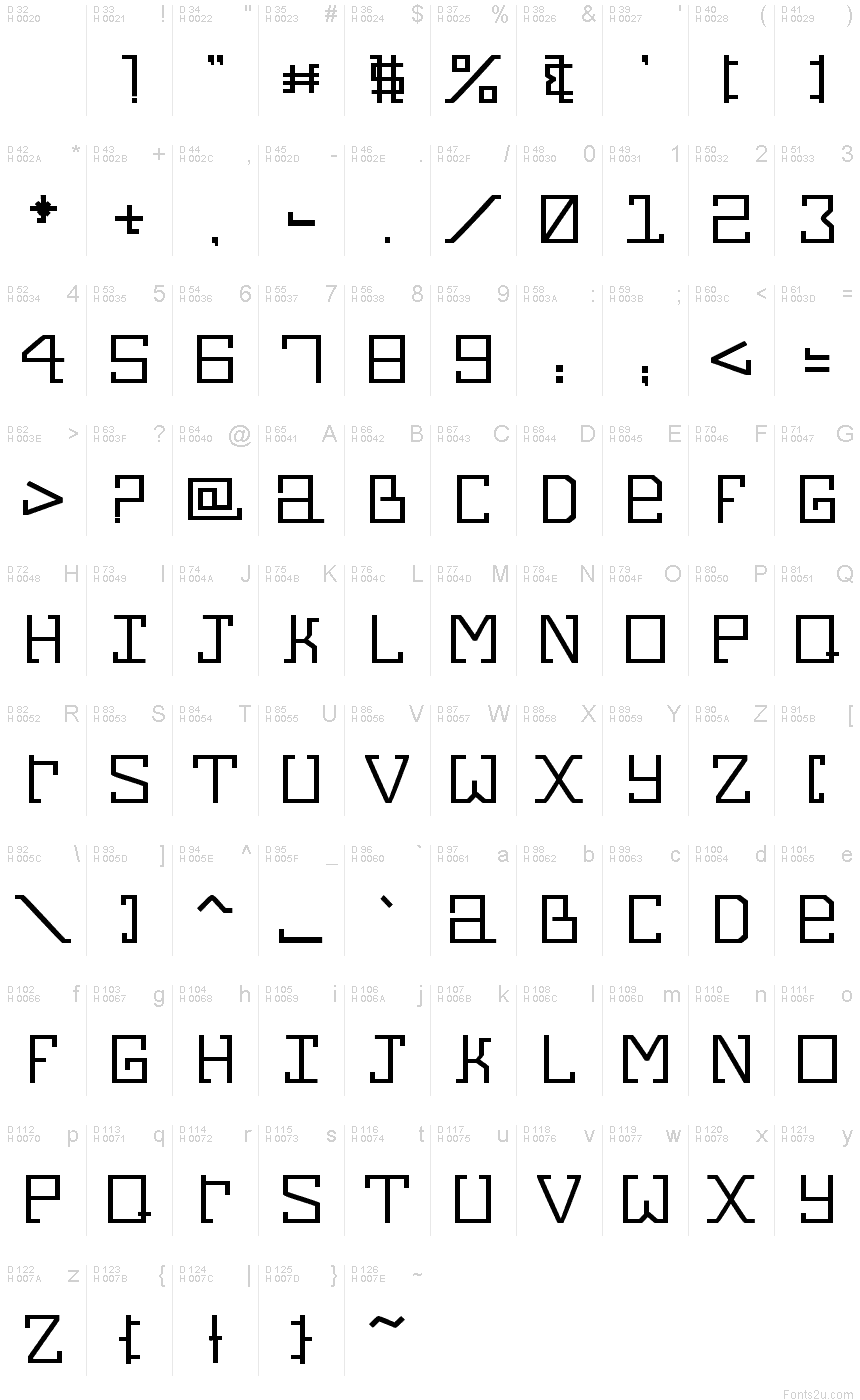
由 Zogoz 的 Andrew Hungerford 设计的 Alphecca 是一款免费的科技感显示字体,看起来就像直接从数字网格中雕刻出来的一样。它的字母高挑、方正,结构紧凑,锋利的 90 度转角既有机械感又出奇地清晰易读。均匀的笔画粗细带来了霓虹灯般的视觉清晰度,赋予每个单词冷静、严谨的工程美感。
使用 Alphecca,您可以打造出适用于科幻界面、游戏 Logo、合成器波(synthwave)海报、科技活动传单以及未来感专辑封面的标题。这款免费字体在大字号下表现尤为出色,其棱角分明的几何形状和垂直张力能够尽情舒展并引人注目。对于正文或辅助信息,建议搭配一款简单的几何无衬线字体,以保持版面整洁,同时让 Alphecca 承担起主要的视觉冲击任务。